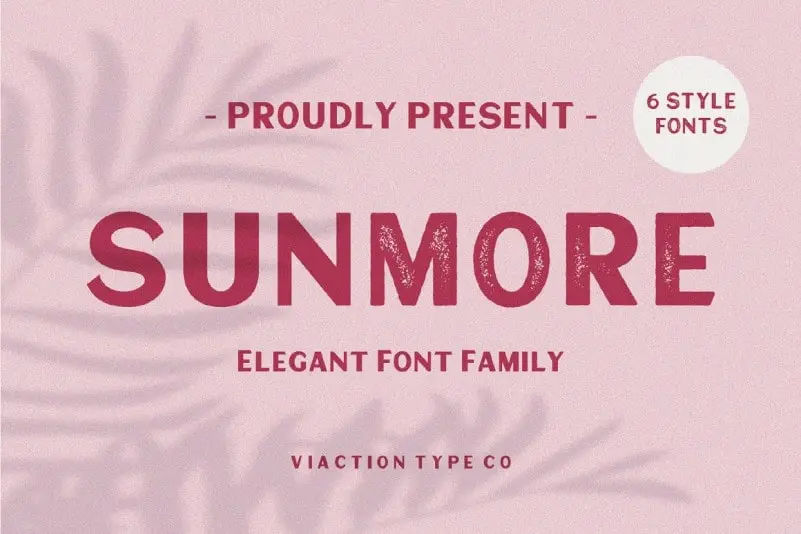
Sunmore Slant Display Font – Download Grátis
A Sunmore Slant Display Font é uma fonte de display sem serif criada pela Viaction Type com uma aparência marcante e decorativa. Seu estilo bold e condensado dá um toque inovador às letras, combinando o moderno do sans-serif com a elegância dos elementos gráficos stampados. Esta fonte é perfeitamente adequada para trabalhos de design elegantemente vintage, oferecendo uma variedade de seis estilos para criar designs diversos. Além disso, ela inclui acréscimos multilíngues, tornando-a ainda mais versátil e acessível. Ideal tanto para designers profissionais quanto para aqueles iniciantes que desejam dar um toque único a suas criações digitais, a Sunmore Slant Display Font é uma escolha inteligente para quem busca uma fonte única e estilizada. Com sua ampla gama de personalização, é perfeita para criar design gráfico elegante ou vintage sem perder o charme moderno do sans-serif.